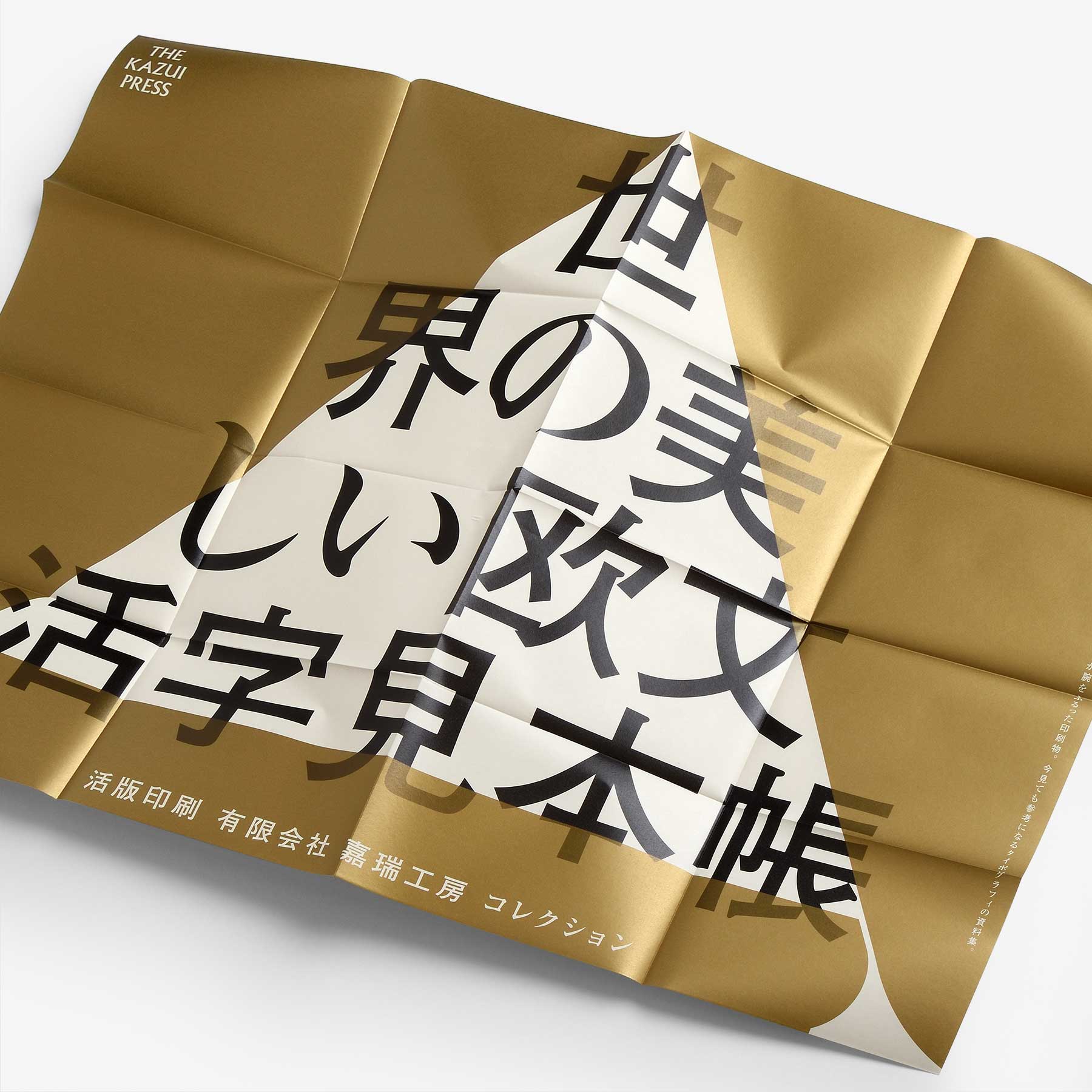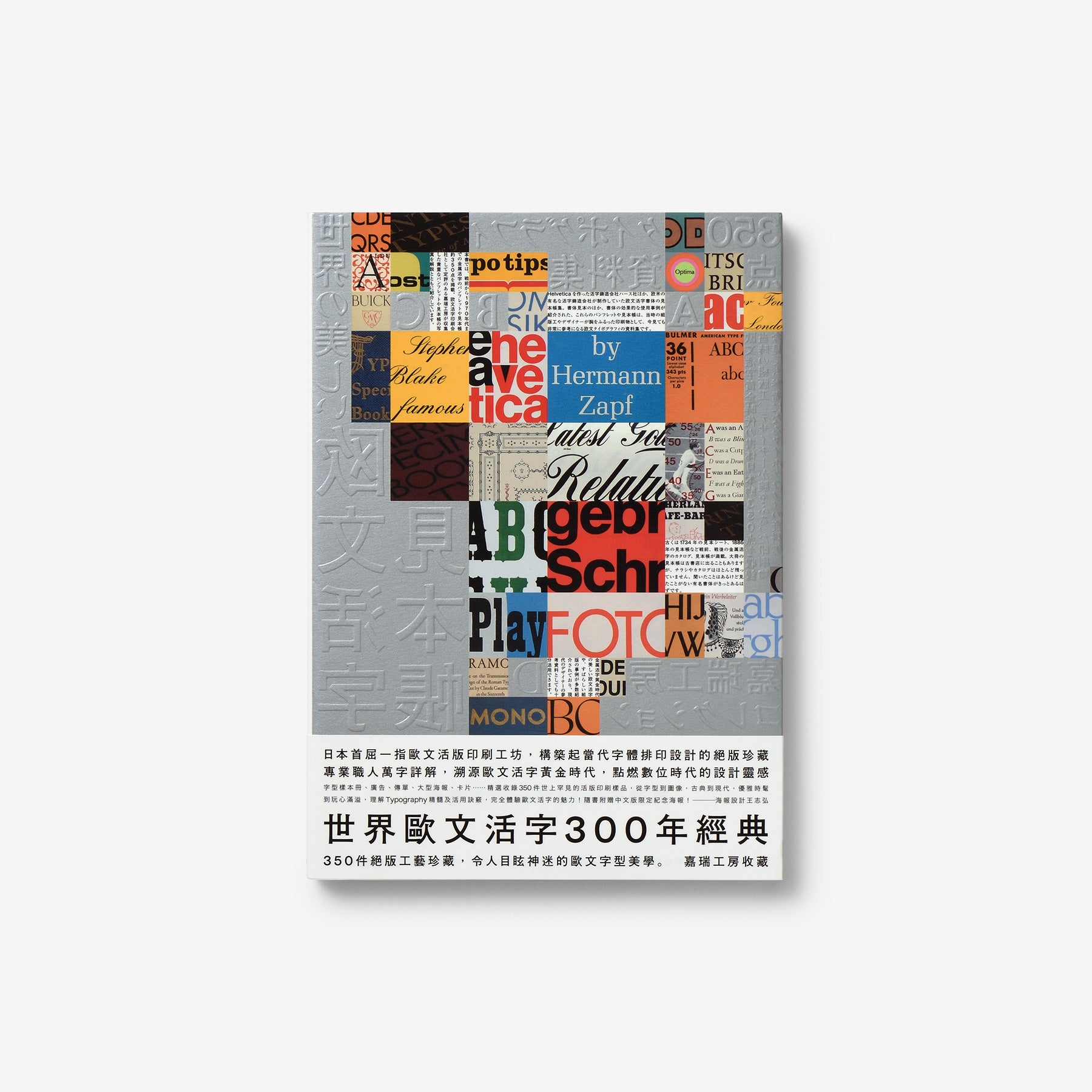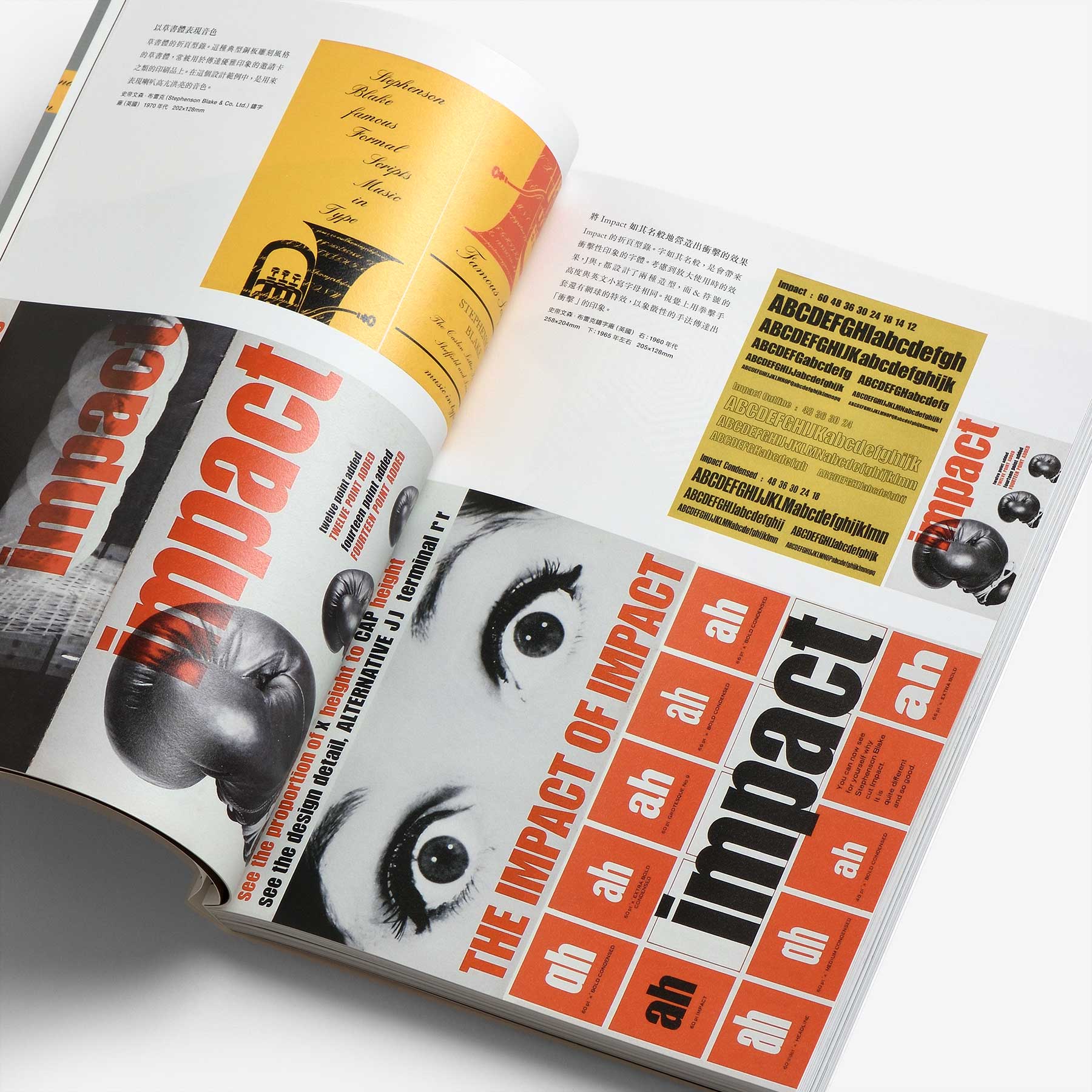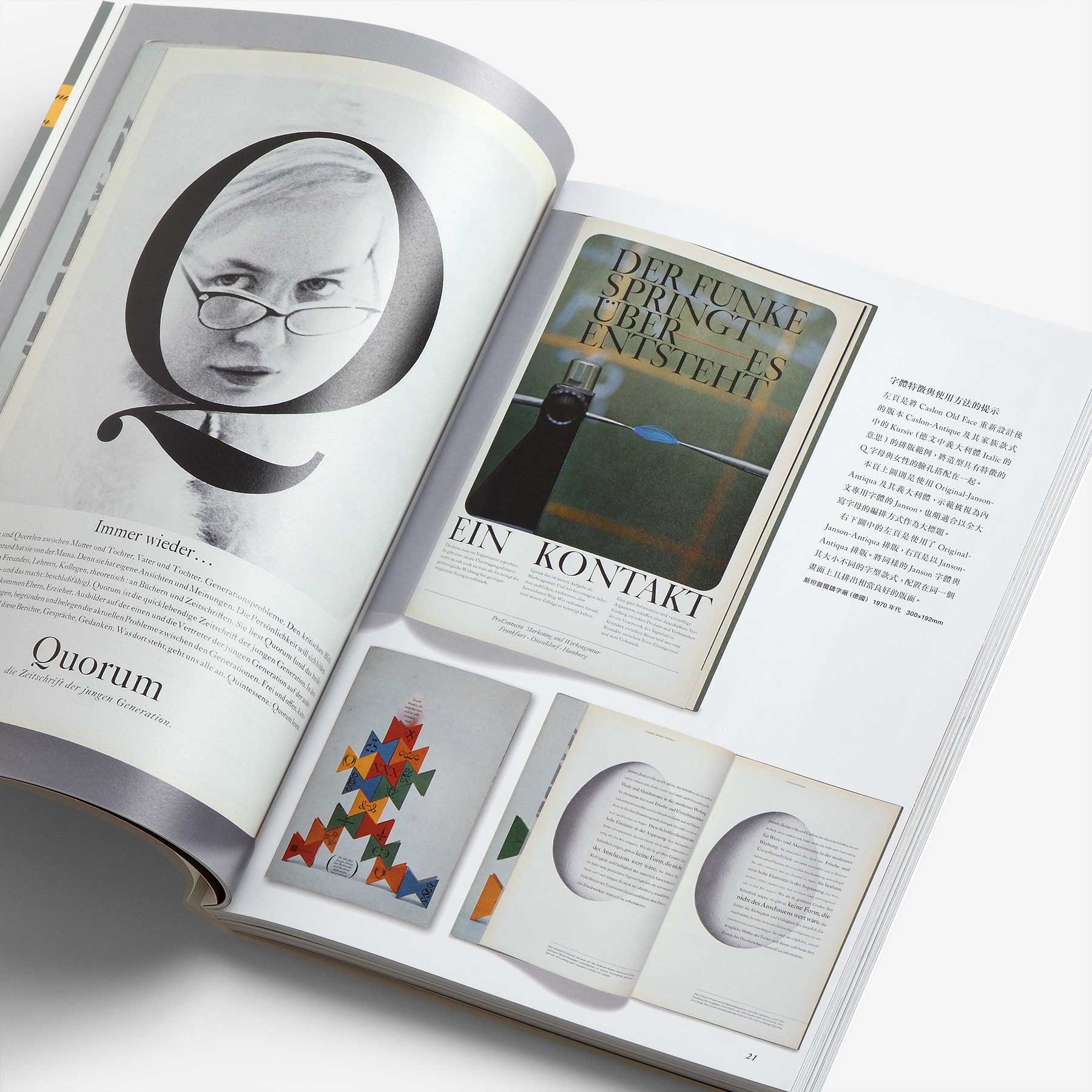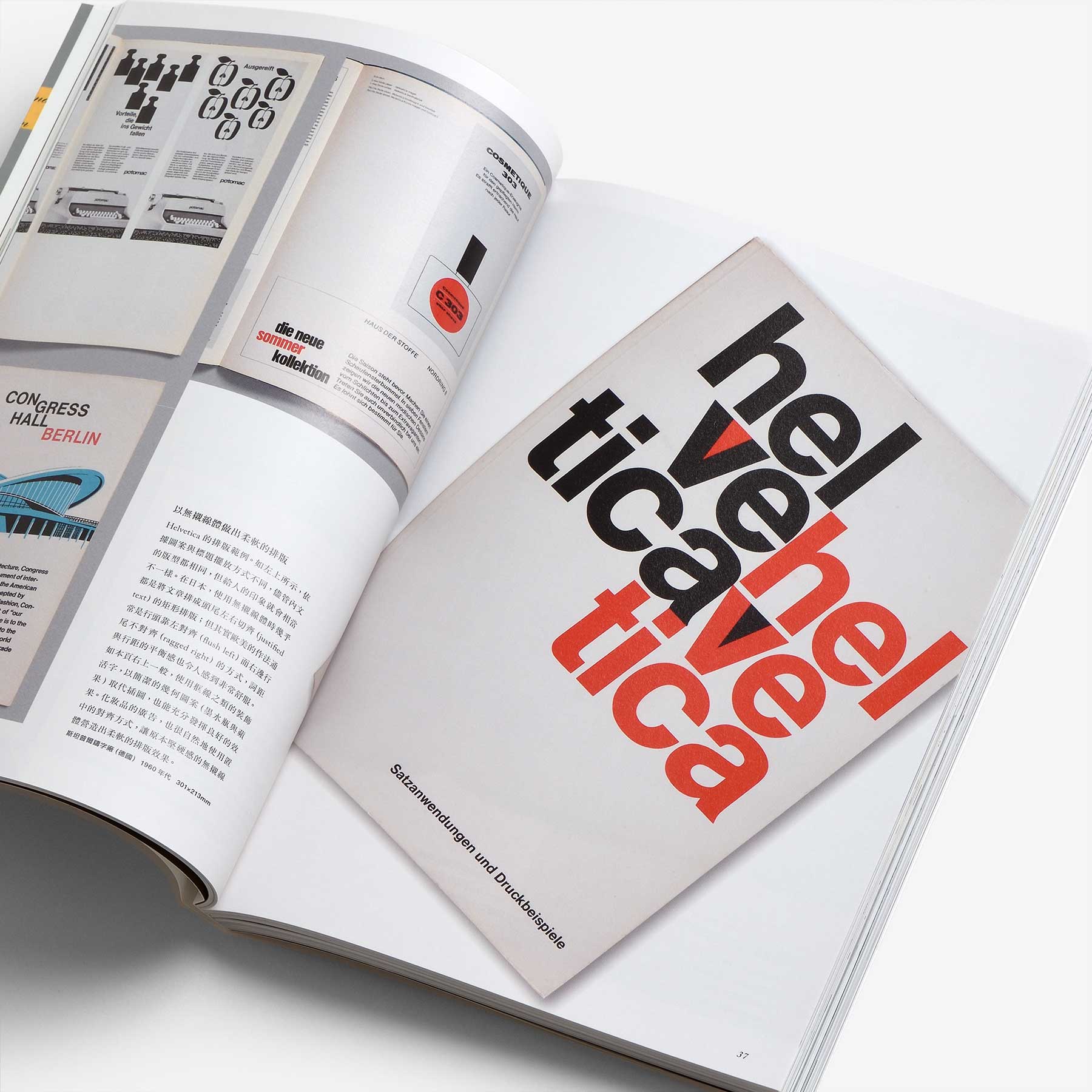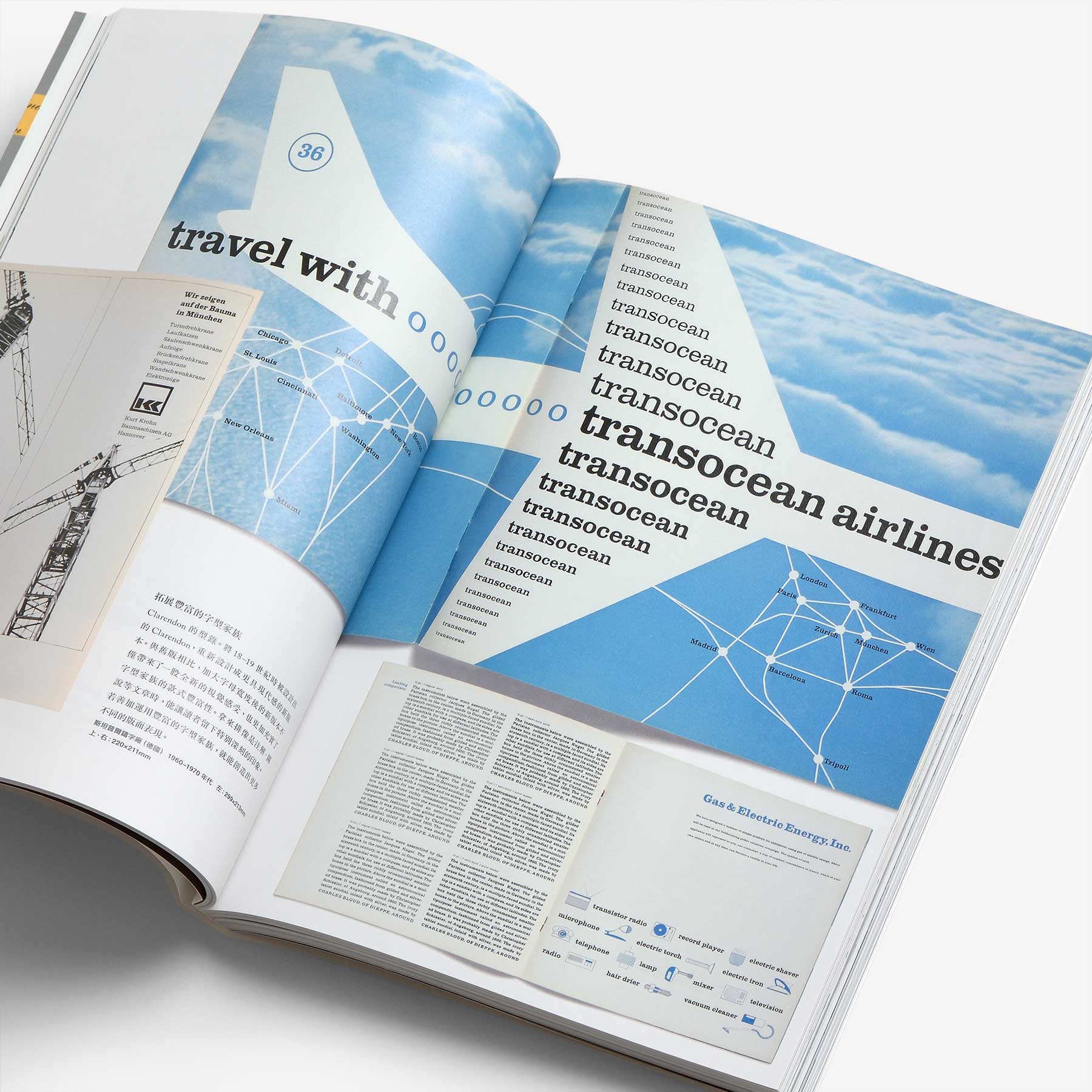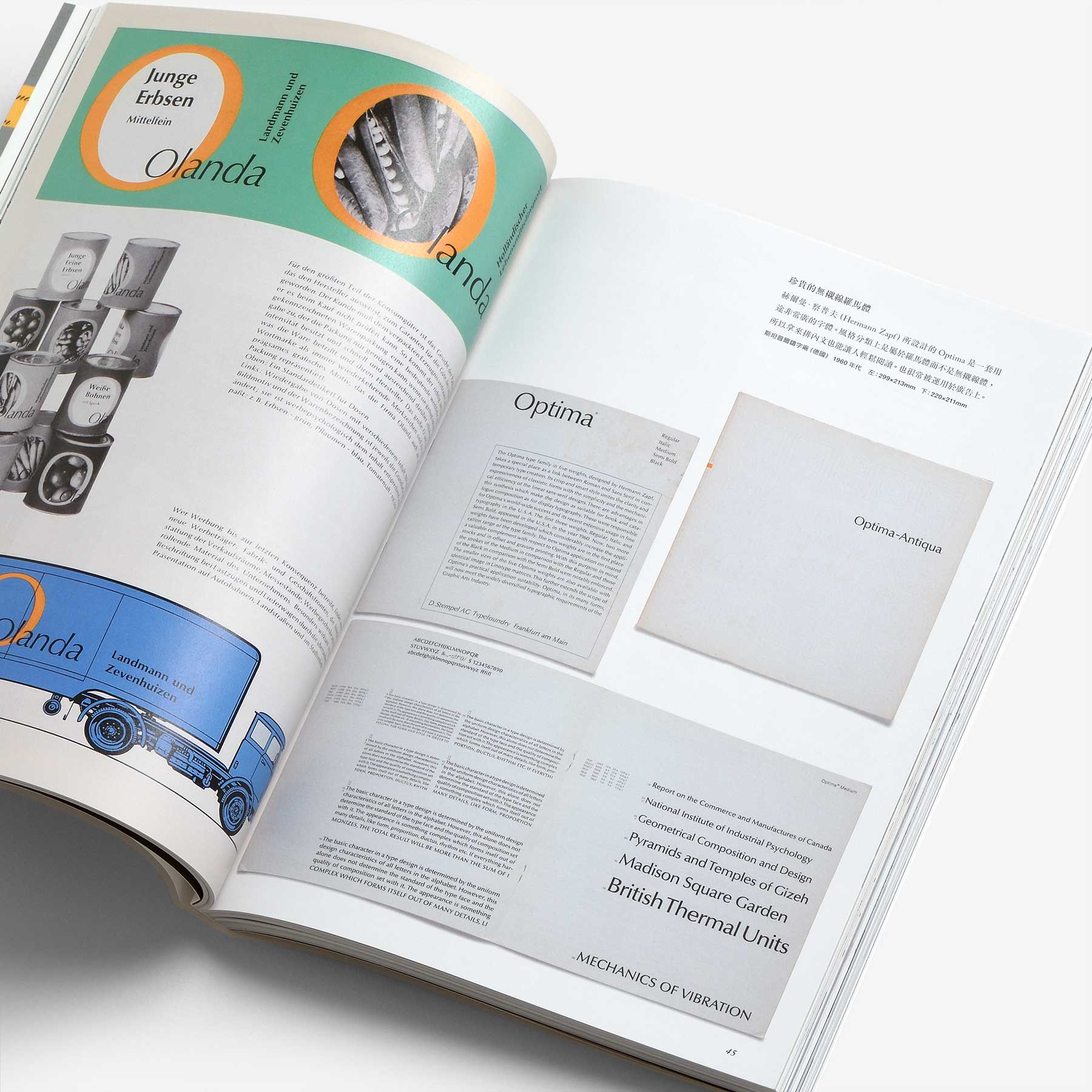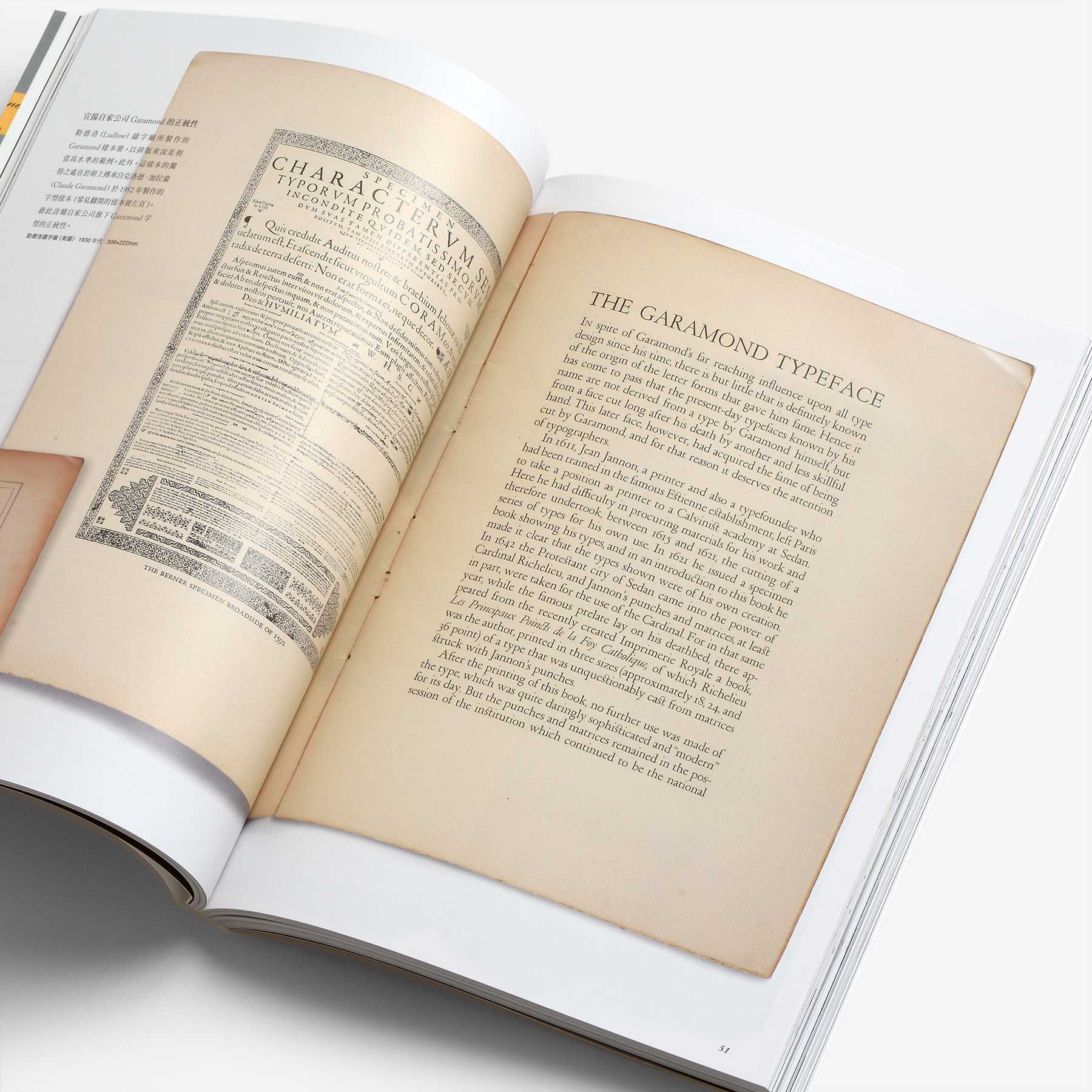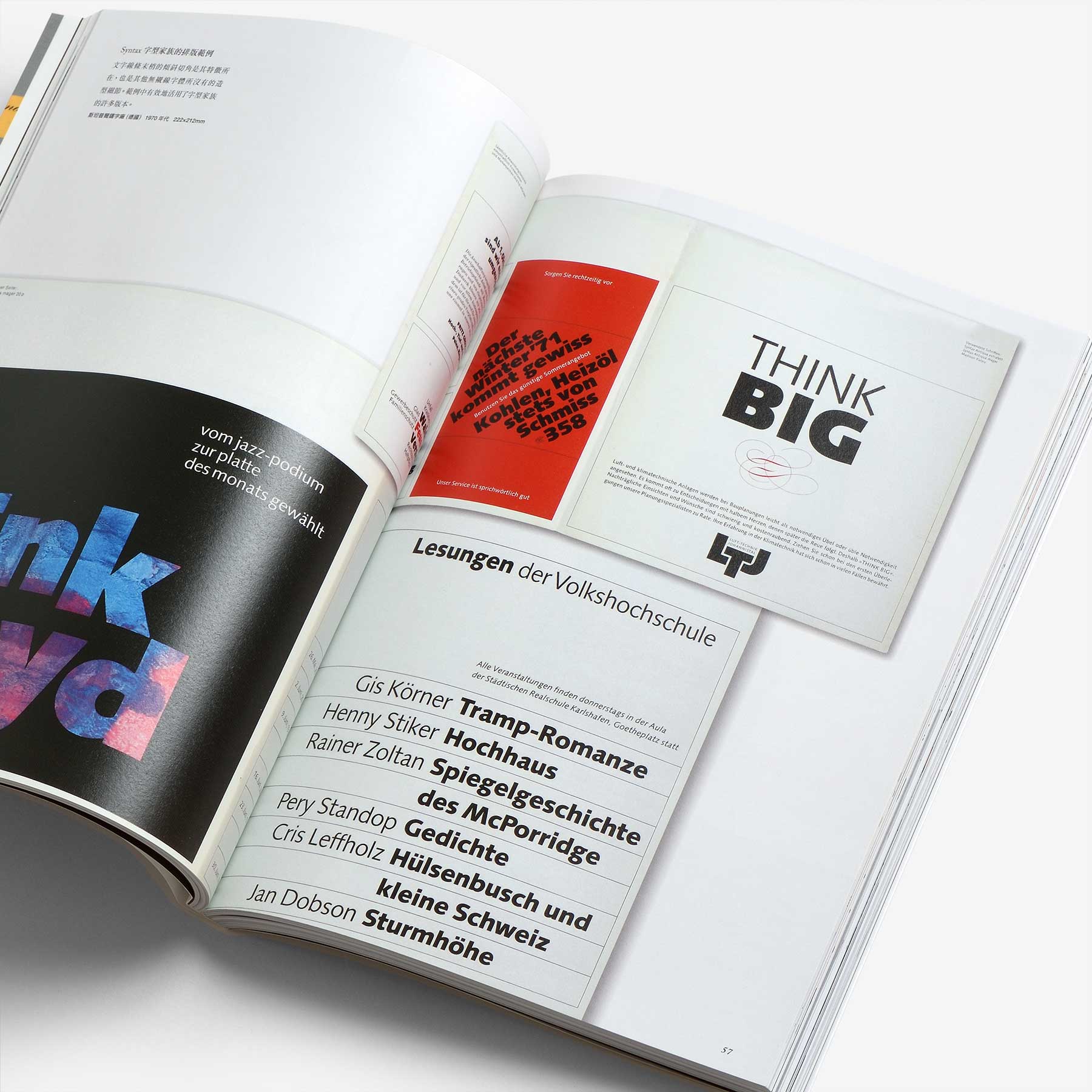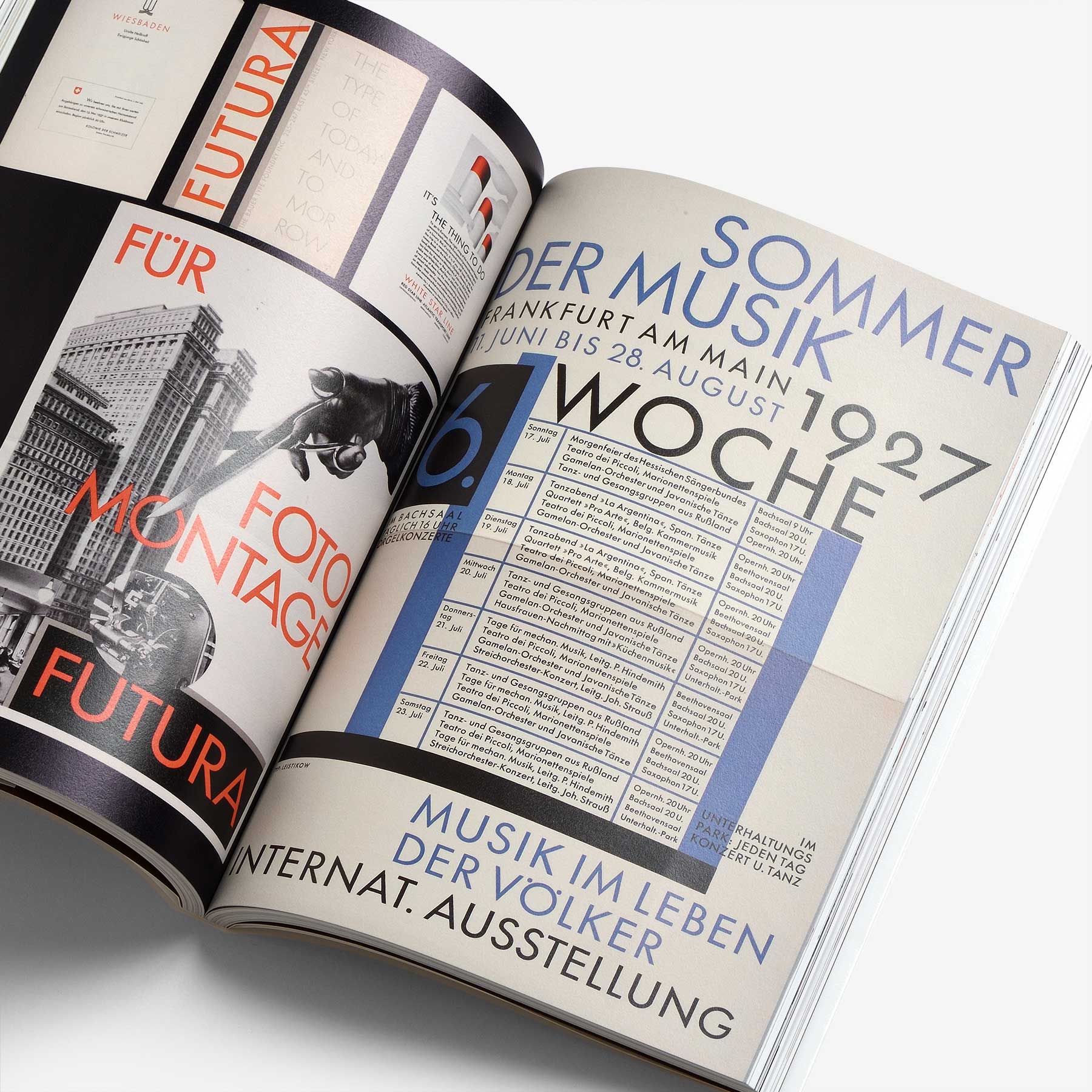
世界歐文活字300年經典(世界の美しい欧文活字見本帳)
2012年に日本で出版された「世界の美しい欧文活字見本帳」の台湾版。台湾のグラフィックデザイナー、王志弘(Wang Zhi-Hong)がデザインしたポスターが付属しています。欧米の活字鋳造会社が制作していた活字書体の古い見本帳やパンフレットなど、活版印刷会社の嘉瑞工房(The Kazui Press)が収集した貴重な資料が約350点掲載されています。
ポスターデザイン: 王志弘 (Wang Zhi-Hong)